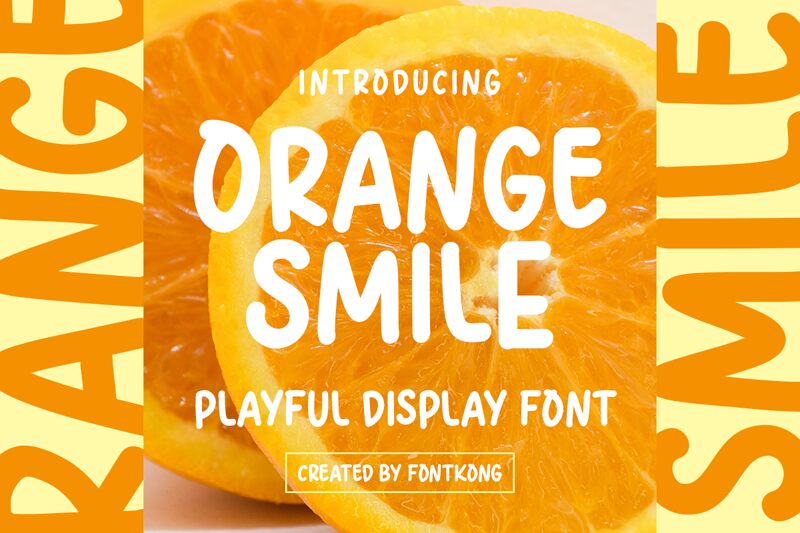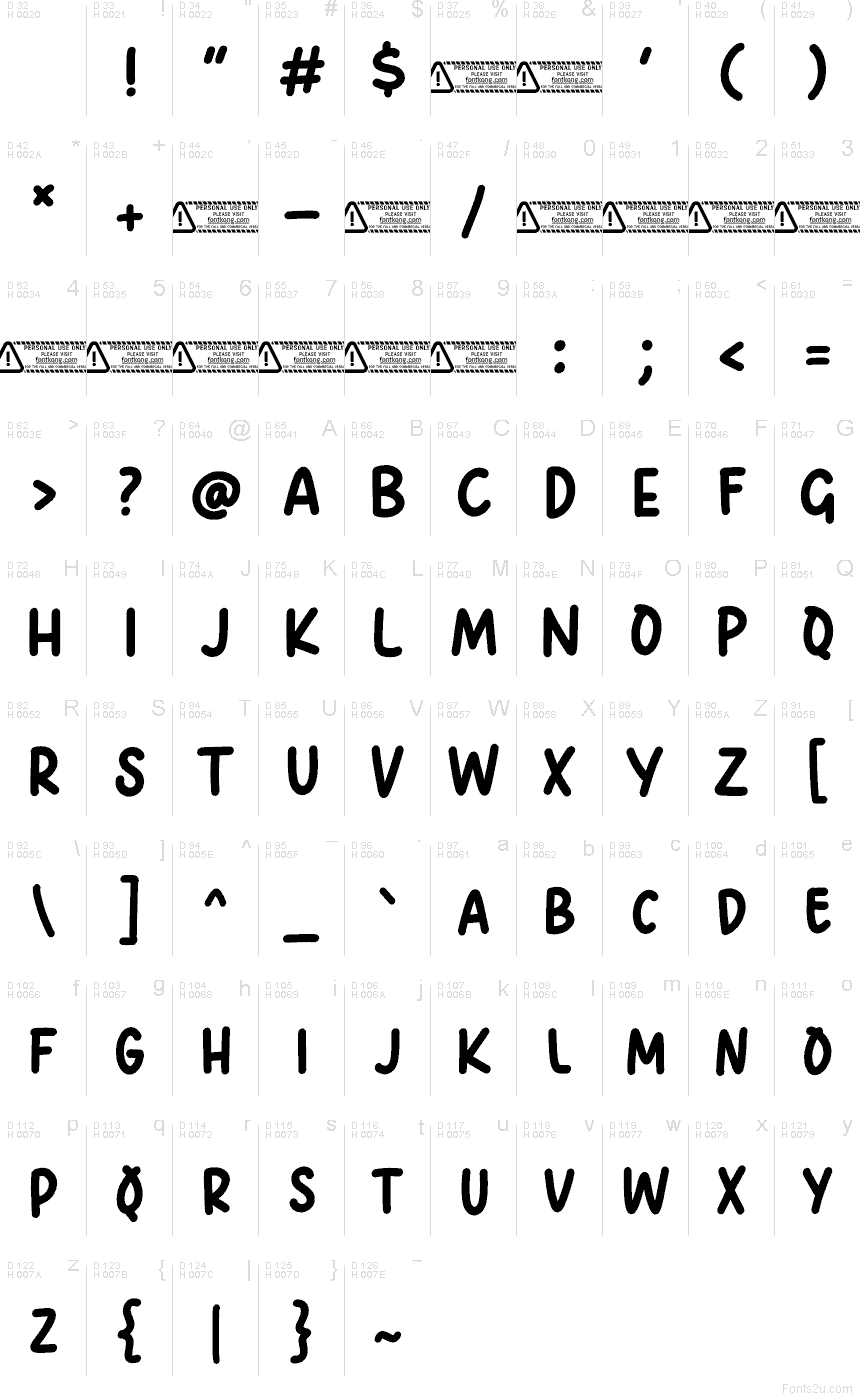
Orange Smile, di Kong Font, è un font display gratuito in stile fumetto, caratterizzato da grandi lettere maiuscole arrotondate e da un ritmo dinamico e manuale. Le lettere trasmettono allegria e sono volutamente un po' irregolari: i tratti spessi, le curve morbide e le forme imperfette rendono questo font giocoso anziché levigato.
È perfetto per il branding destinato ai bambini, confezioni di snack, inviti a feste, titoli di poster e post sui social media dove si desidera un font gratuito che comunichi calore e spontaneità invece di una perfezione artificiosa. Usalo per titoli brevi, copertine o semplici loghi: le lettere maiuscole corpose e il ritmo leggermente traballante regalano un sorriso immediato alle brevi frasi.